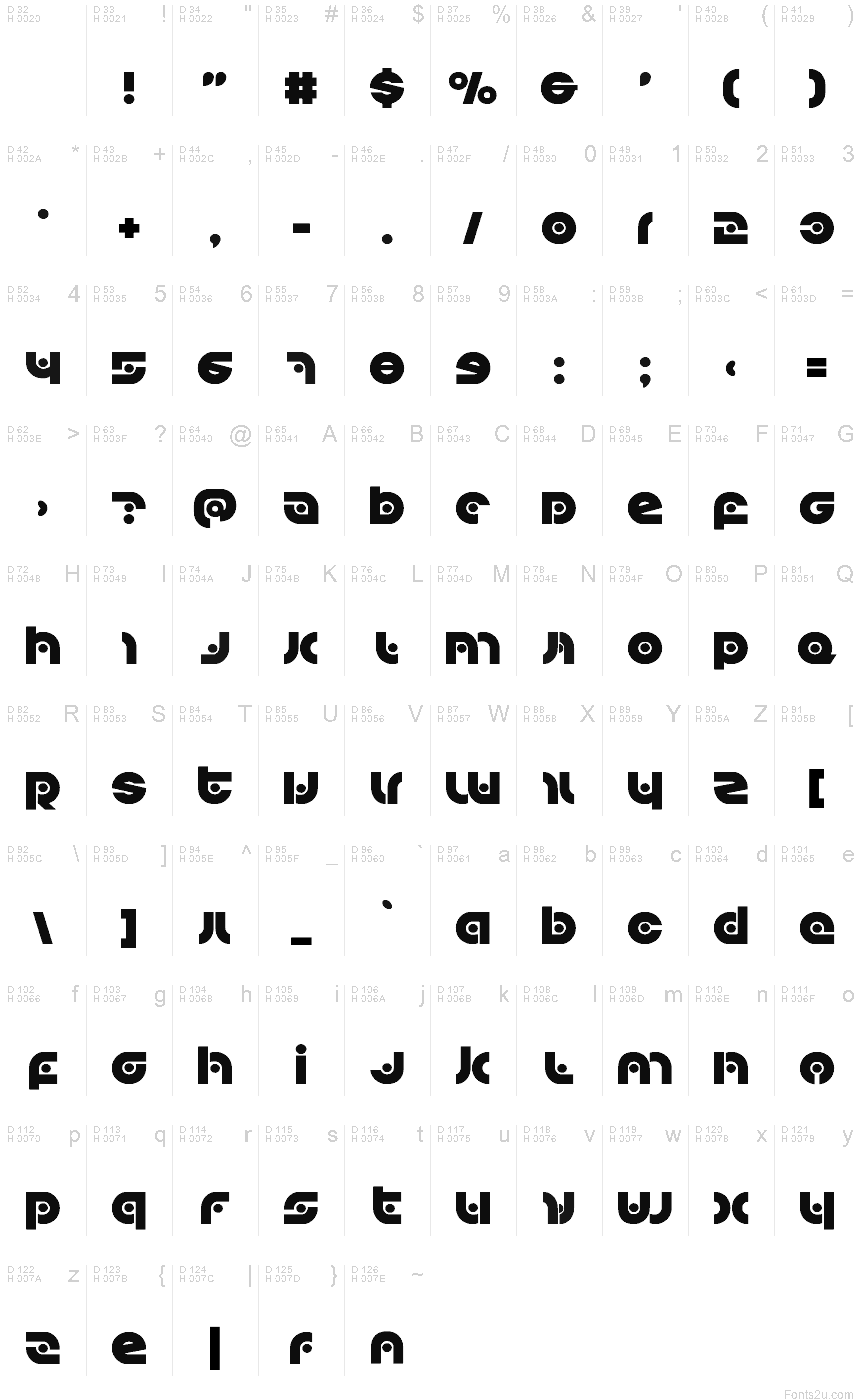
Kovacs Spot
Kovacs Spot od Iconian Fonts to futurystyczny, groovowy krój pisma typu display o wyrazistym, kolistym rytmie. Każda litera przypomina obracającą się płytę, przeciętą i przebitą ostrymi wycięciami, które świecą niczym porty konsoli z filmów sci-fi. Grube, nasycone kreski i ciasne krzywizny tworzą silny wizualny rytm, sprawiając, że nawet krótkie słowa wyglądają jak logo.
Kovacs Spot idealnie nadaje się do nagłówków na ulotkach EDM, retro-futurystycznych plakatach, tytułach gier, w brandingu technologicznym, aplikacjach oraz na eksperymentalnych okładkach albumów. Ten darmowy font najlepiej sprawdza się w dużych rozmiarach, gdzie jego okrągłe otwory i masywne sylwetki mogą w pełni wybrzmieć. Połącz go z czystym, geometrycznym krojem bezszeryfowym w tekście głównym i pozwól Kovacs Spot przejąć kontrolę nad najbardziej przyciągającymi wzrok elementami.